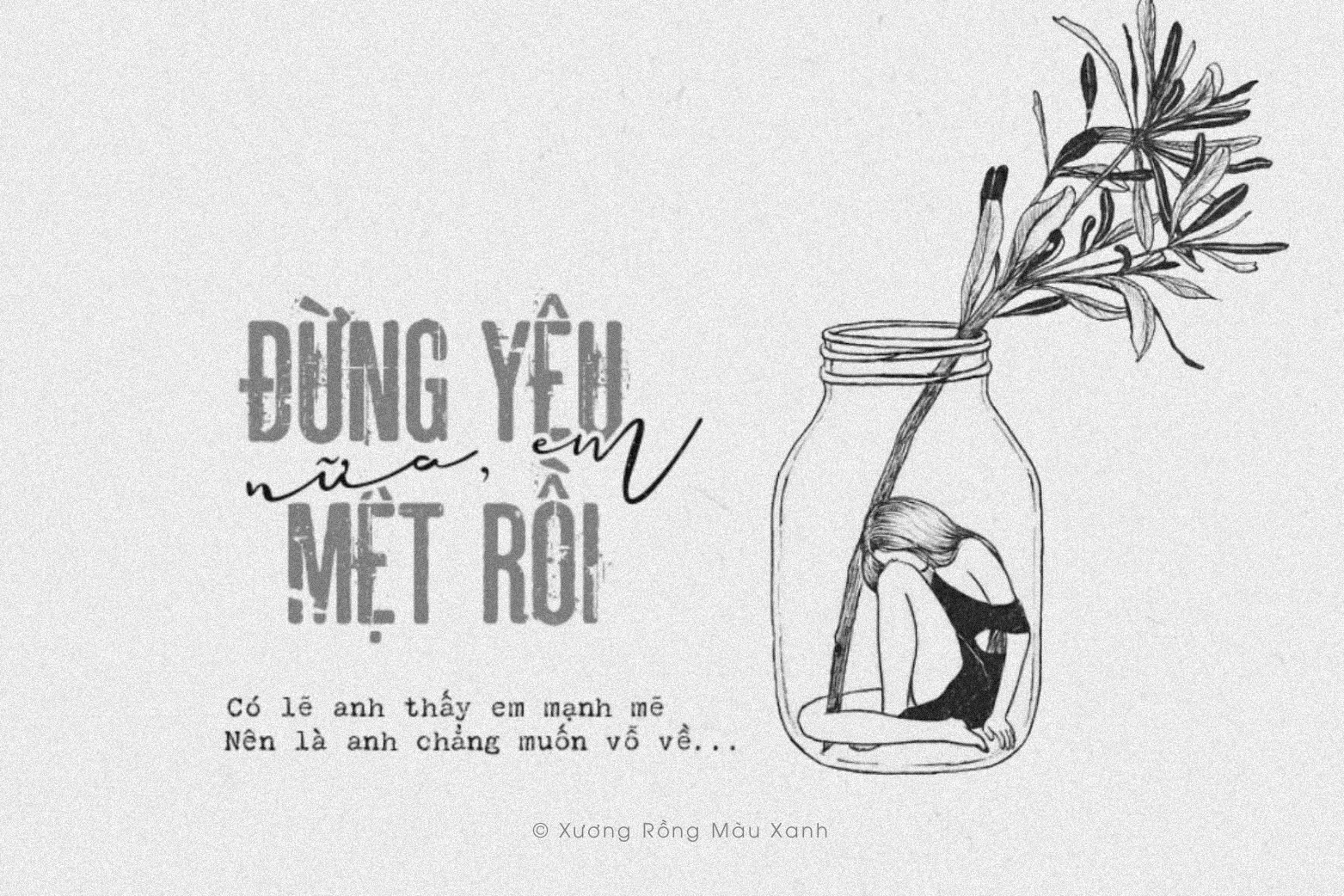
Font MTD Hello Paris Script Việt hóa là một kiểu chữ mang đậm nét mềm mại, duyên dáng và đầy cảm xúc, được thiết kế để mô phỏng nét viết tay thanh mảnh nhưng đầy bay bổng. Với các đường cong uốn lượn tinh tế và các ký tự kết nối mượt mà, font chữ này lý tưởng cho các thiết kế mang hơi hướng lãng mạn, nhẹ nhàng như thiệp cưới, bìa sách, trích dẫn tâm trạng, poster hoặc branding cá nhân.
Phiên bản Việt hóa đã được tối ưu hóa đầy đủ dấu tiếng Việt mà vẫn giữ nguyên tinh thần của bản gốc – vừa nghệ thuật vừa dễ đọc. Các ký tự viết tay tự nhiên giúp người dùng truyền tải cảm xúc chân thật, thân mật qua từng dòng chữ.
MTD Hello Paris Script Việt hóa sẽ là lựa chọn lý tưởng cho những ai đang tìm kiếm một kiểu chữ thanh lịch nhưng vẫn mang cá tính nhẹ nhàng và sâu lắng.